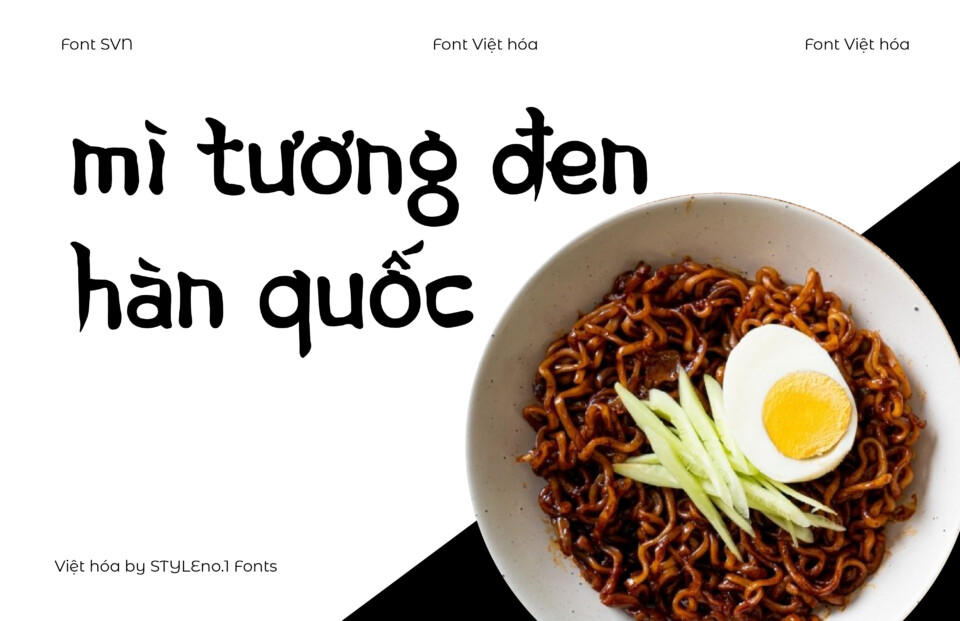
Font Việt hóa SVN Korean Calligraphy – Đỉnh cao nghệ thuật thư pháp Hàn Quốc cho thiết kế nội dung học tập
Giới thiệu về Font Việt hóa SVN Korean Calligraphy
Trong thế giới đồ họa hiện đại, việc lựa chọn bộ Font Miễn Phí phù hợp đóng vai trò quan trọng giúp nâng cao giá trị thẩm mỹ cho tác phẩm. Font Việt hóa SVN Korean Calligraphy là một bộ phông chữ độc đáo, mang đậm phong cách thư pháp truyền thống của xứ sở Kim Chi. Được tinh chỉnh kỹ lưỡng để hỗ trợ đầy đủ tiếng Việt, bộ font này giúp các bạn học sinh và giáo viên dễ dàng tạo ra những tài liệu học tập, bài thuyết trình hay thiệp chúc mừng đầy ấn tượng và giàu cảm xúc.
Đặc điểm nổi bật của Font Việt hóa SVN Korean Calligraphy
Phong cách thiết kế uyển chuyển
Font Việt hóa SVN Korean Calligraphy sở hữu những nét bút lông mạnh mẽ nhưng không kém phần mềm mại. Từng ký tự được mô phỏng theo lối viết tay thủ công, tạo cảm giác chân thực và gần gũi. Đây là lựa chọn lý tưởng cho các dự án liên quan đến văn hóa Đông Á, bìa sách nghệ thuật hoặc các ấn phẩm giáo dục cần sự sáng tạo. Font chữ này không chỉ đẹp về mặt thị giác mà còn đảm bảo sự đồng nhất trong bố cục văn bản.
Khả năng ứng dụng đa dạng trong học đường
Với bộ Font Việt hóa SVN Korean Calligraphy, các em học sinh có thể tự tay thiết kế các poster câu lạc bộ hoặc trang trí báo tường sinh động. Đối với giáo viên, phông chữ này hỗ trợ đắc lực trong việc trình bày các bài giảng về lịch sử, nghệ thuật hoặc ngôn ngữ, giúp thu hút sự chú ý của học sinh hiệu quả hơn. Sự kết hợp giữa nét chữ truyền thống và công nghệ số hóa mang lại trải nghiệm thị giác mới lạ và chuyên nghiệp.
Kết luận và cách sở hữu Font Việt hóa SVN Korean Calligraphy